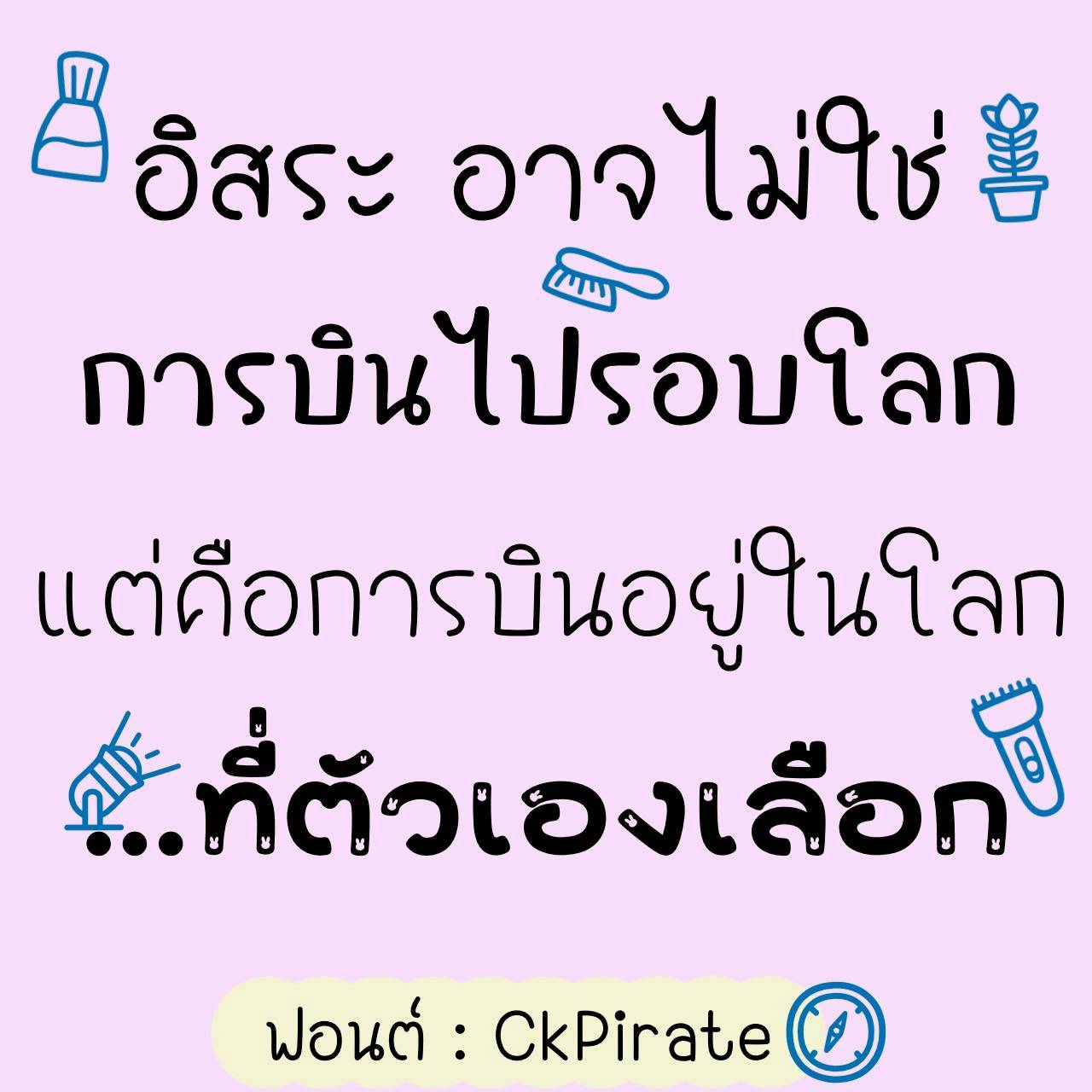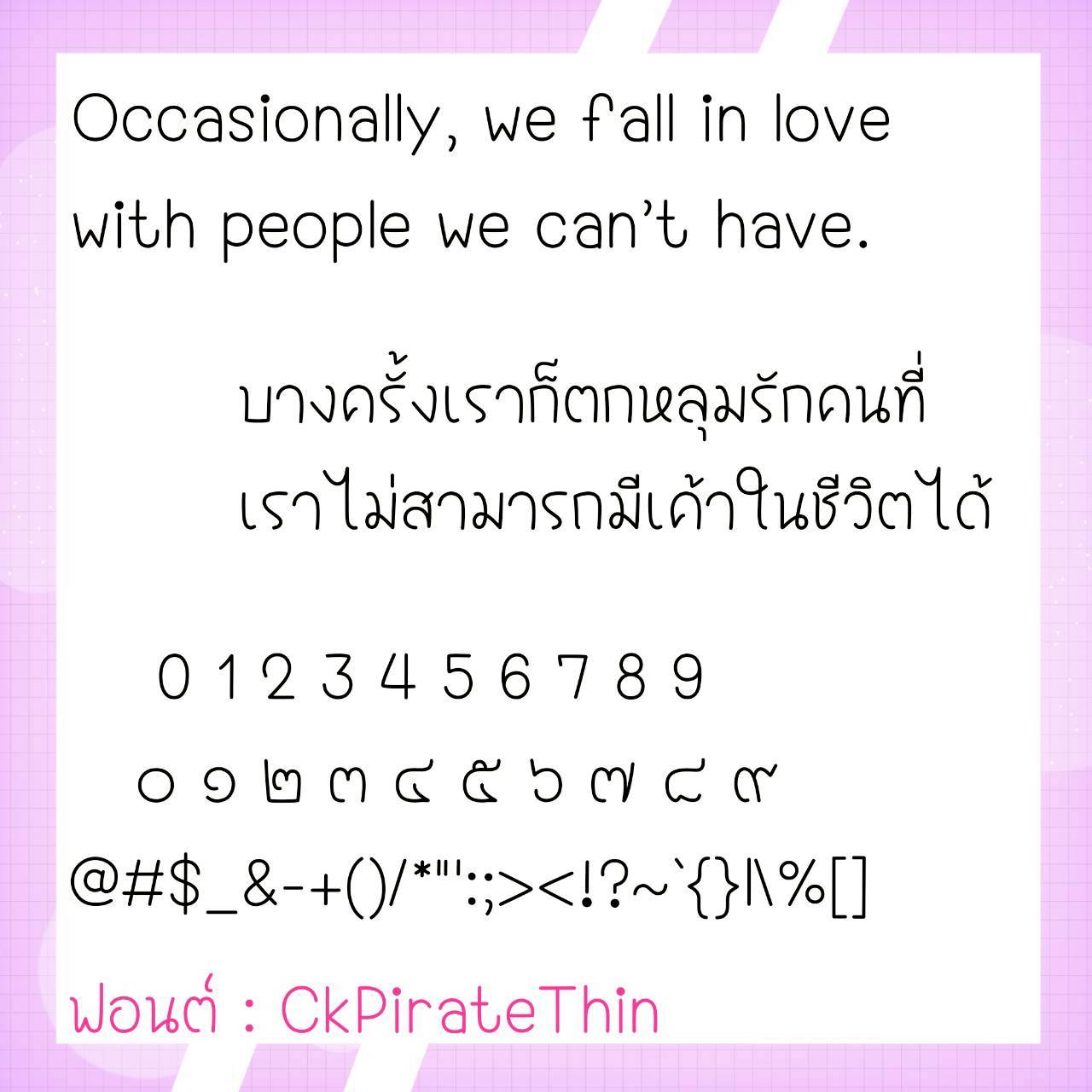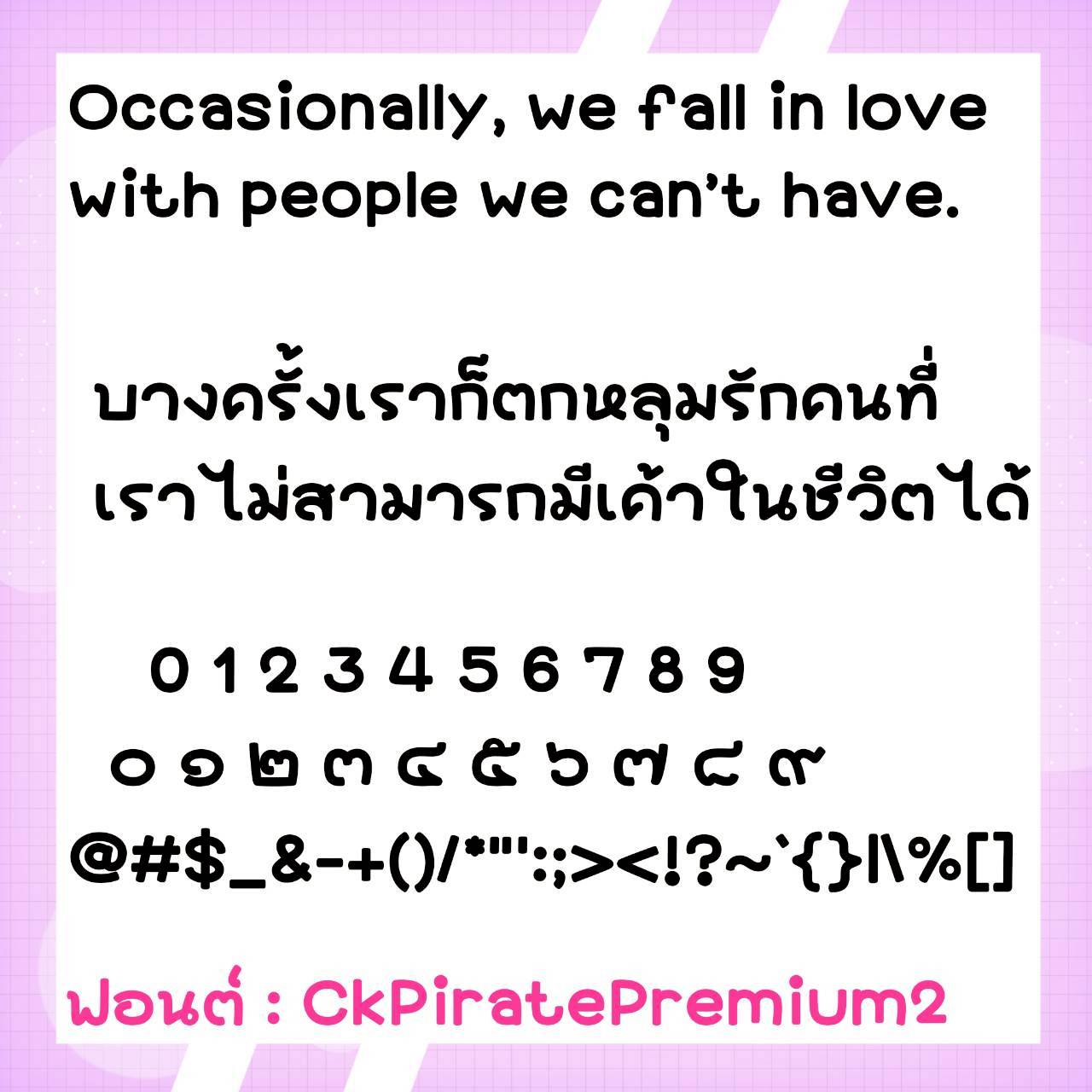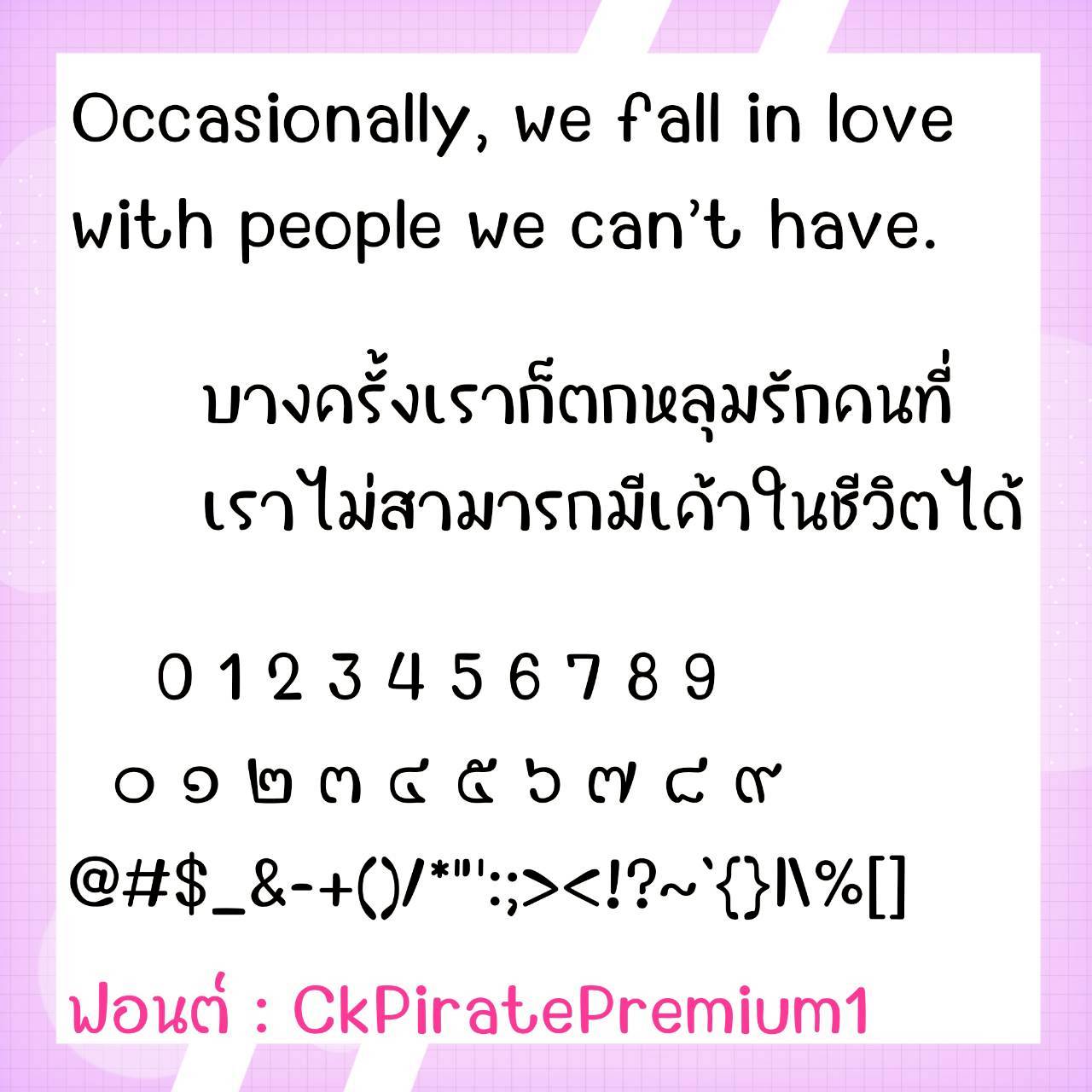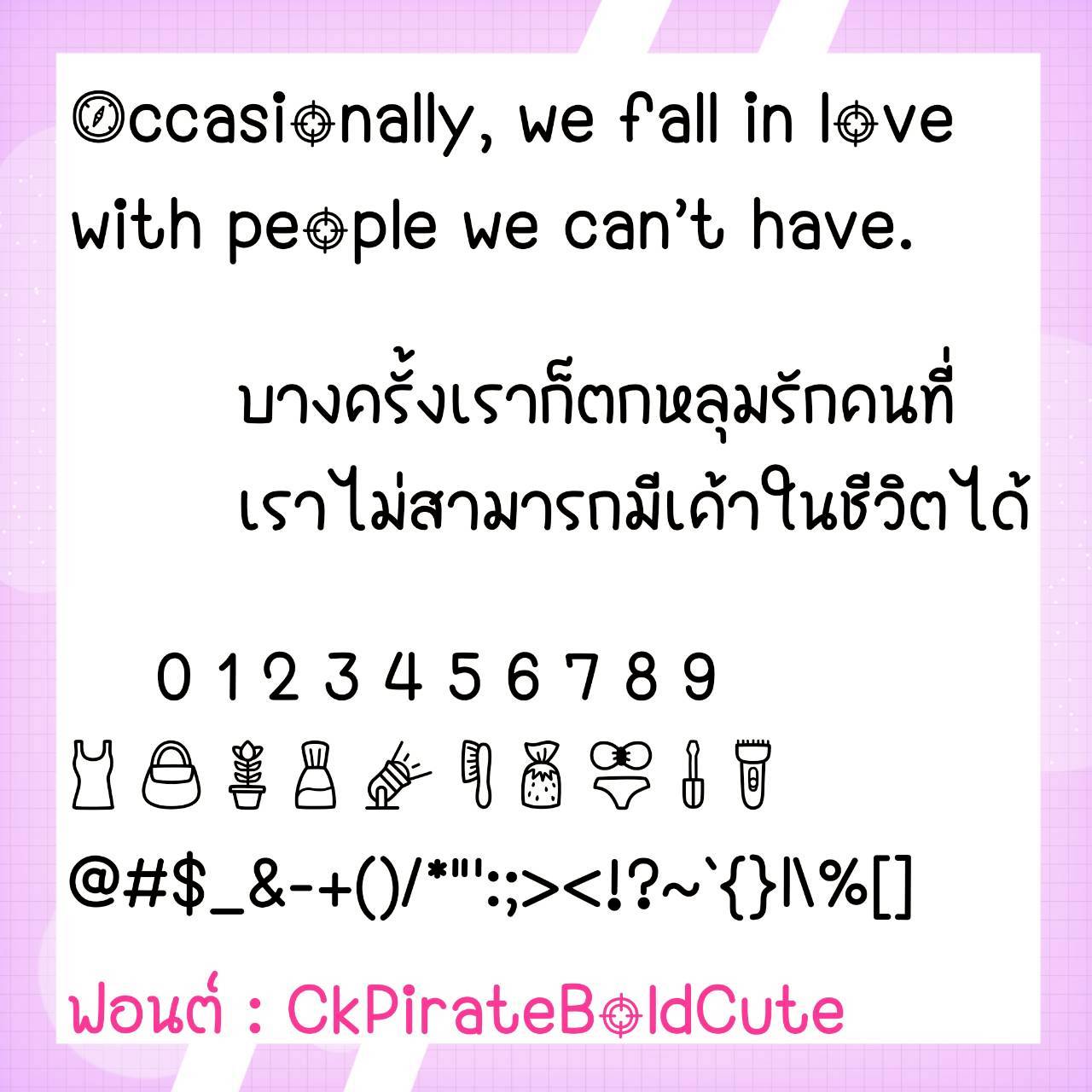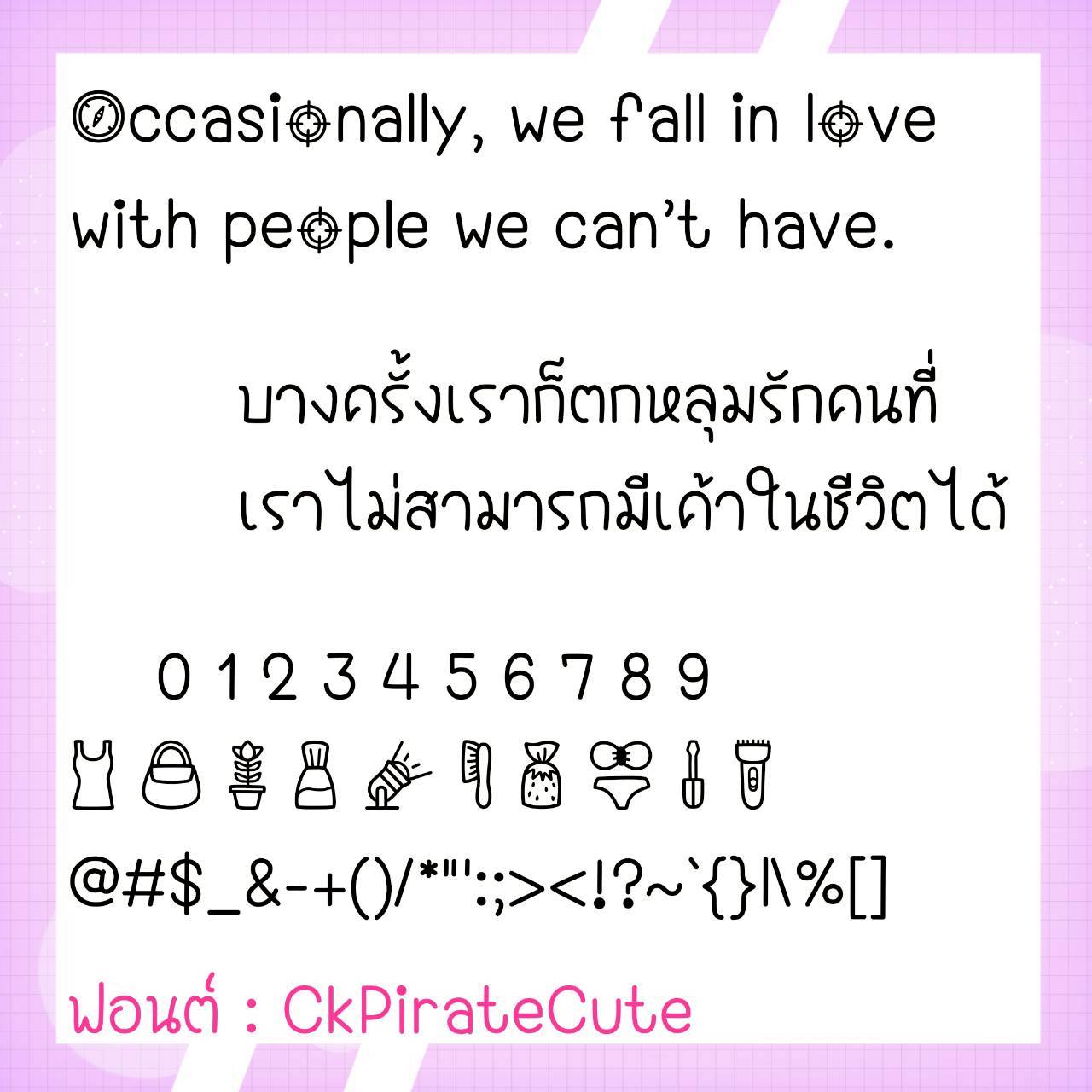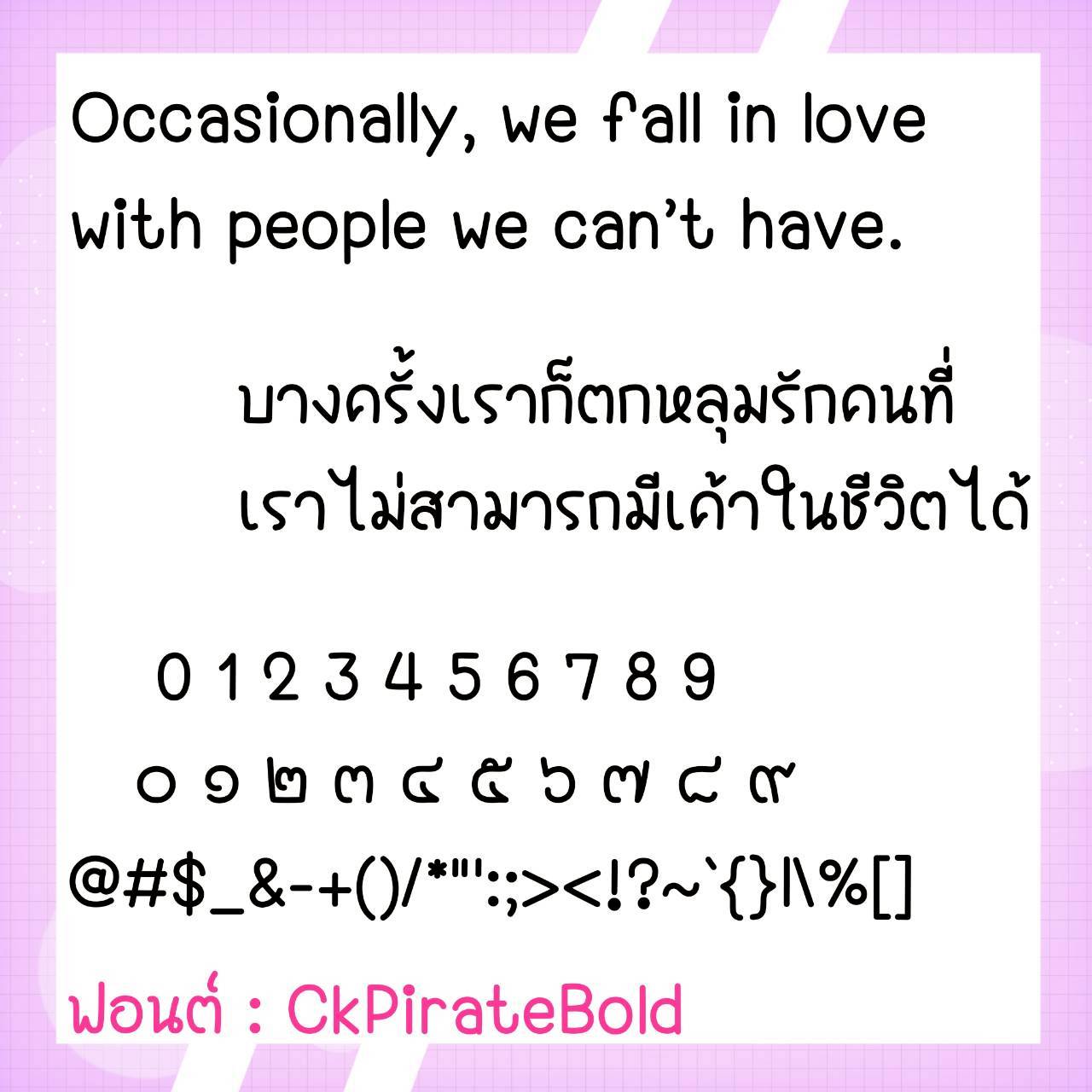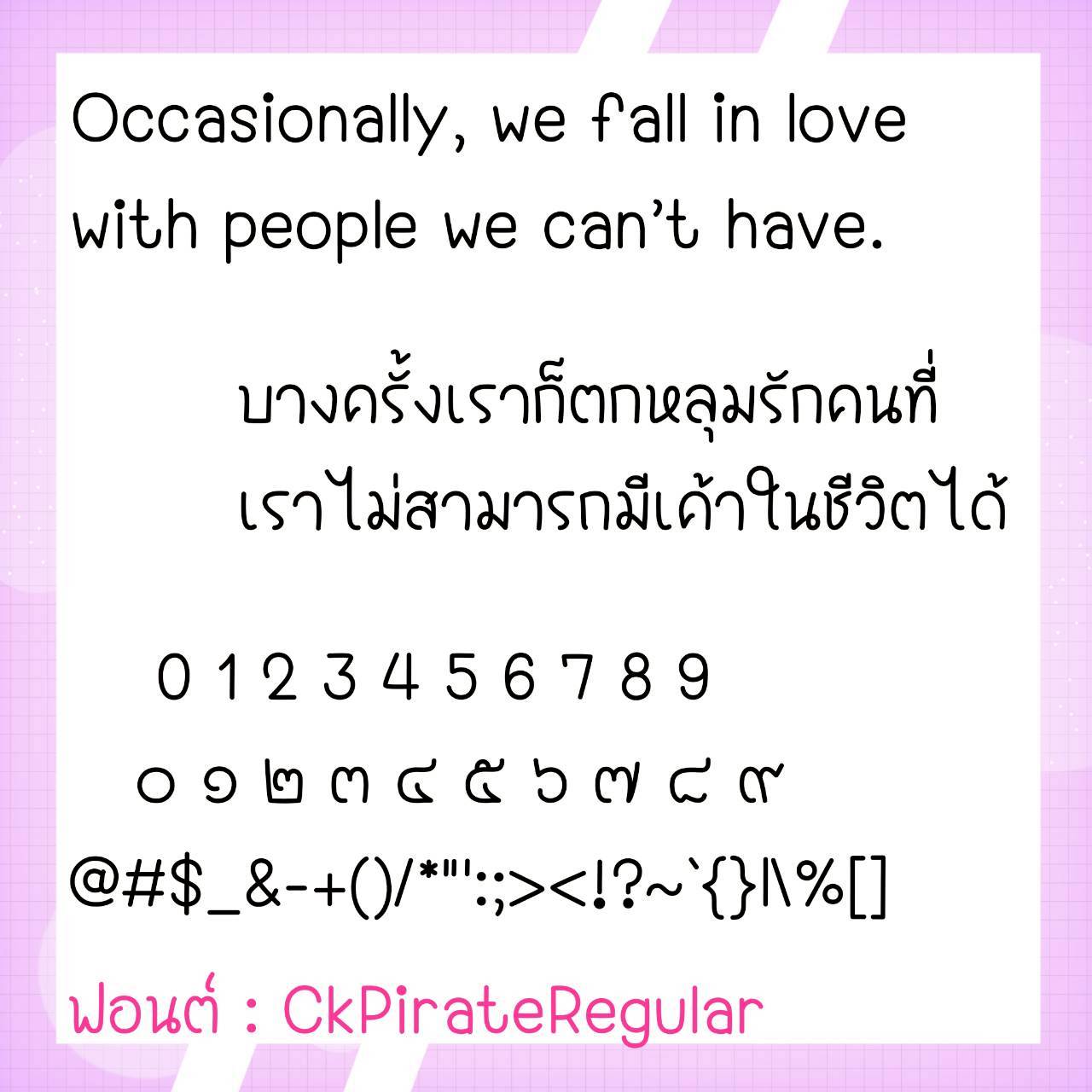
Font CkPirate
🔸 ฟอนต์ลายมือแนวไม่มีหัว ตัวพอดีๆ คล้ายลายมือหวัดๆ แต่ยังเน้นให้อ่านง่าย ใช้งานได้หลากหลาย และยังมีไฟล์อิโมจิน่ารักๆ ที่ใช้แทนเลขไทยให้ด้วยค่ะ 🥰💙
🔹 A handwriting font without a head, with just the right amount of letters, similar to cursive handwriting, but still emphasizing readability, it can be used in many ways, and there are also cute emoji files that can be used instead of Thai numerals. 🥰💙